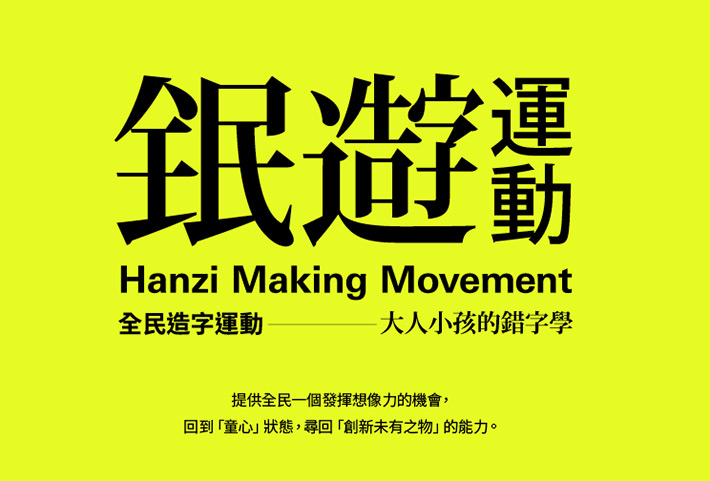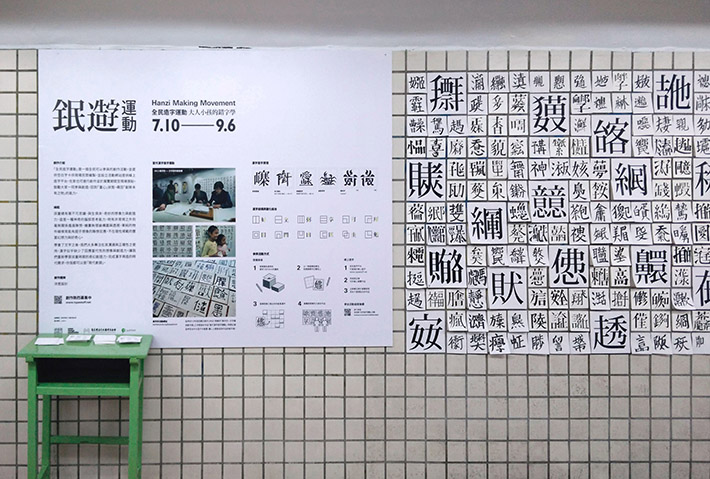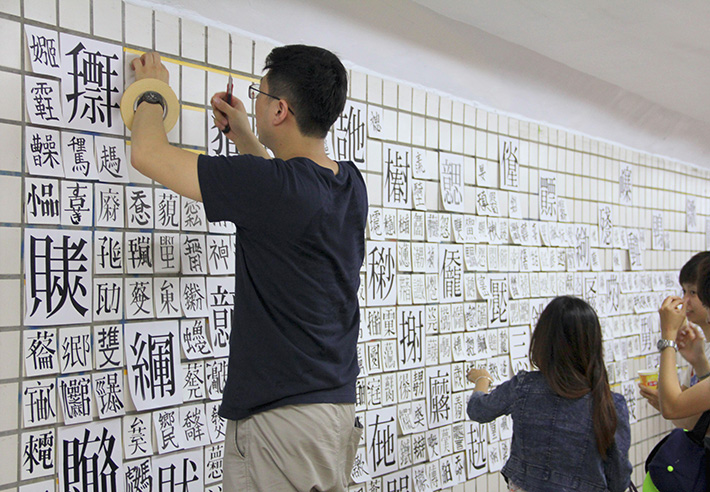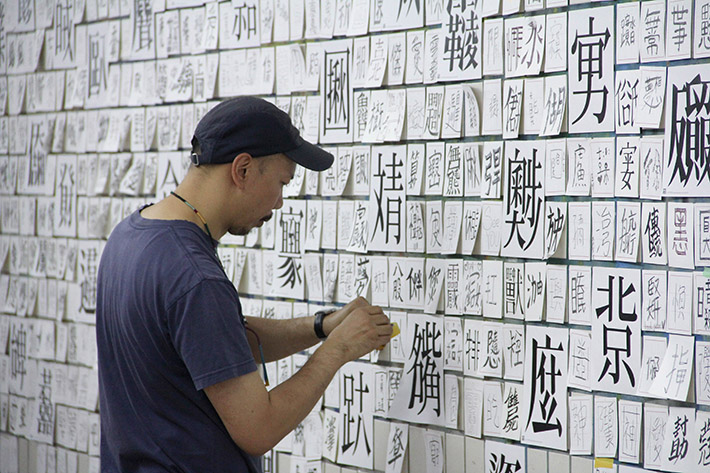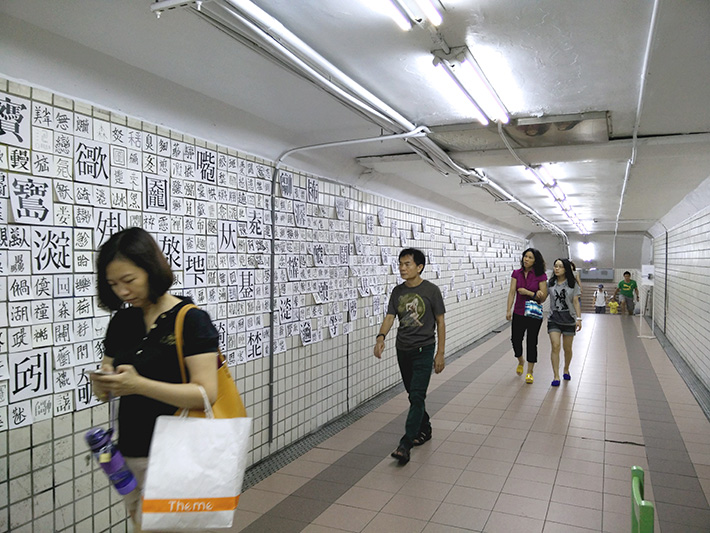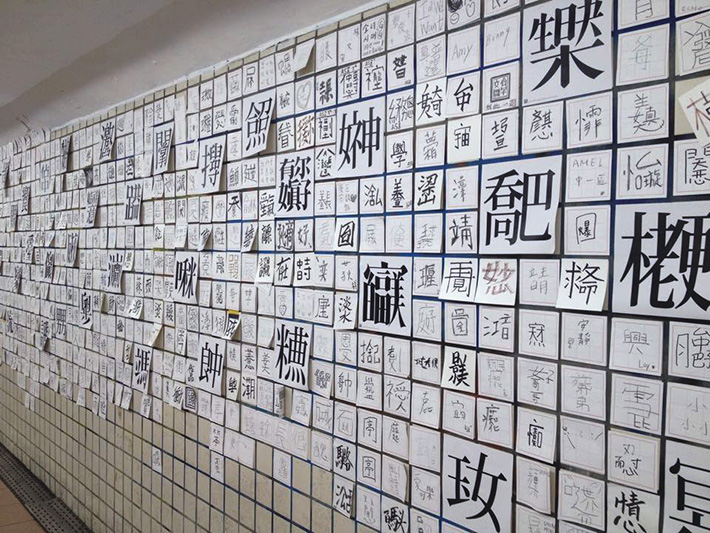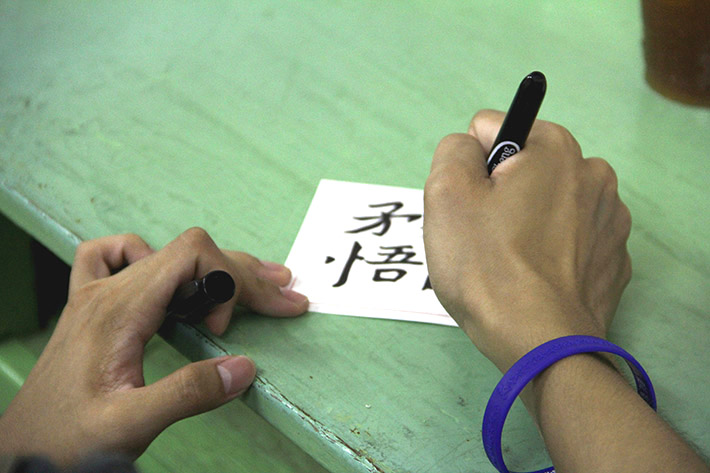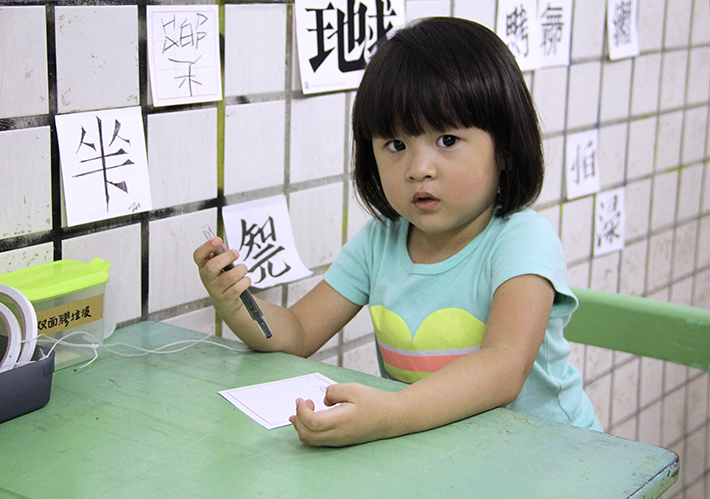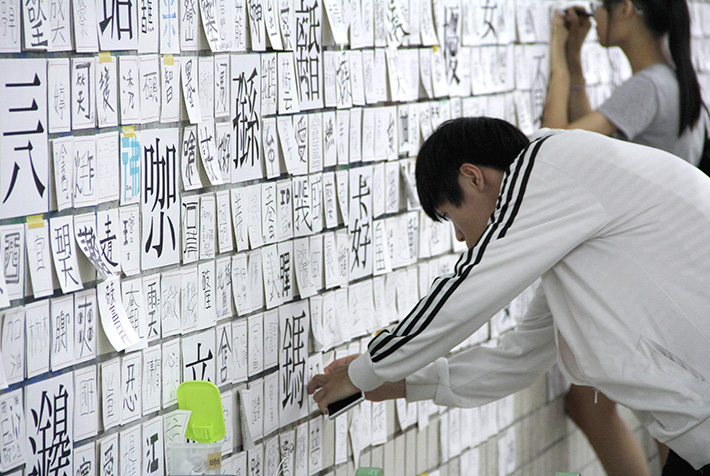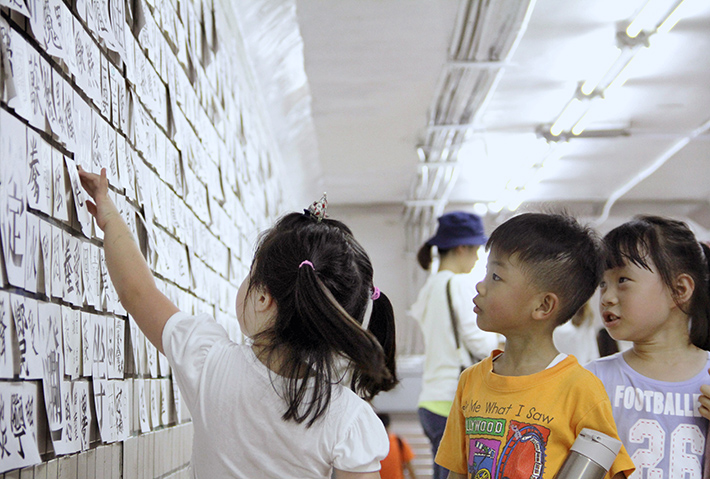
全民造字运动
关於造字运动
孩童总有著不可思议、与生俱来、奇妙的想像力与创造力,这是一种神奇的脑部思考能力, 时有非常规之外的毫无关系遥远联想,绘画无理论构图与透视,单纯的物件线条常能有超乎想像的联想反应, 不在理性规范的丰富幻想力与好奇心。
还记得小时候写错字阶段吗?彷彿也隐藏著对於不熟悉文字养成前的各种想像与创造力; 还记得毕业纪念册上,各种不同风格独异的步步高升、友谊长存……等等文字创作?直到我们学会了文字之后, 多专注在其沟通与正确性之使用,相较於英文总有因应时局不断创造新字產出,汉字似乎缺少了回应当代性的想像与创造力。
延续2012年当代汉字造字运动
田田圈文创与 URS21 策划「疯字形—文字艺术创作展」之作品「当代汉字造字运动」,造成迴响,特将此展延伸至臺中大型户外装置,让人人都能成為作品的创作者。